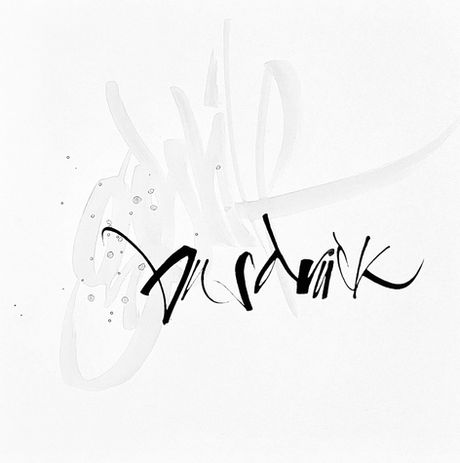
Gestik und Ausdruck
Simone Rahn
GESTIK & AUSDRUCK
Erschaffe Einzigartiges...
Wieviele neue Schriften und Techniken, bis man endlich zufrieden ist? - Dieser Workshop nimmt das bereits Gelernte auf und schöpft gleichzeitig Neues und Eigenes - oder interpretiert Altes neu.
Inhaltlich arbeiten wir mit einem einzigen Wort. Erschaffen es immer wieder neu und anders. Wieviele Varianten davon sind möglich? Damit gehen wir in Serie...
Damit sich auch diese Art der expressiven Schreibweise mit einem haptischen, kalligrafischen Ergebnis verbinden lässt, nehmen wir noch etwas "Gestik" für den Hintergrund mit auf.